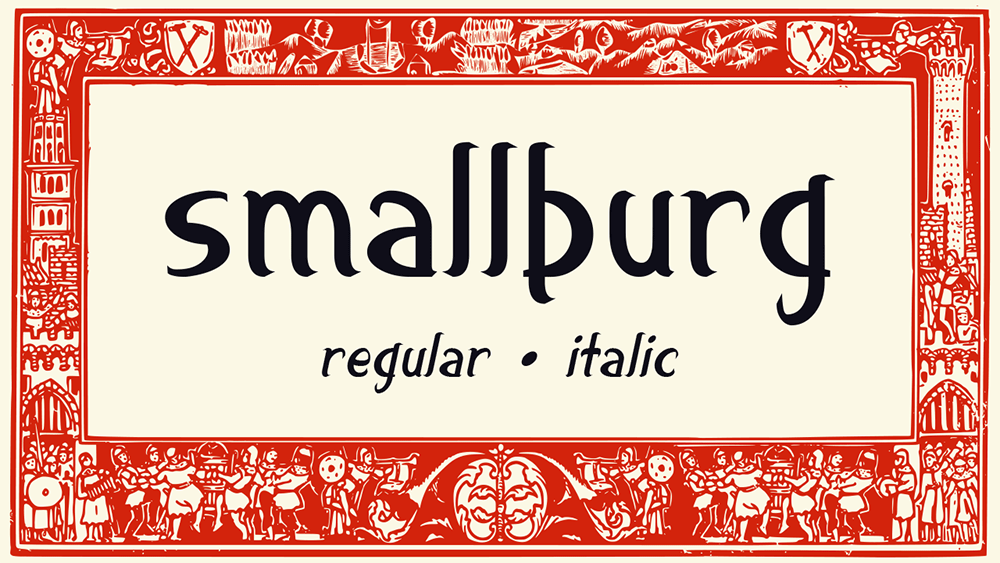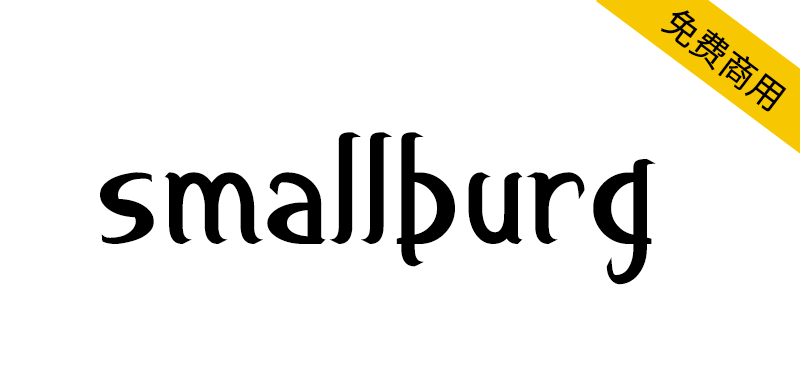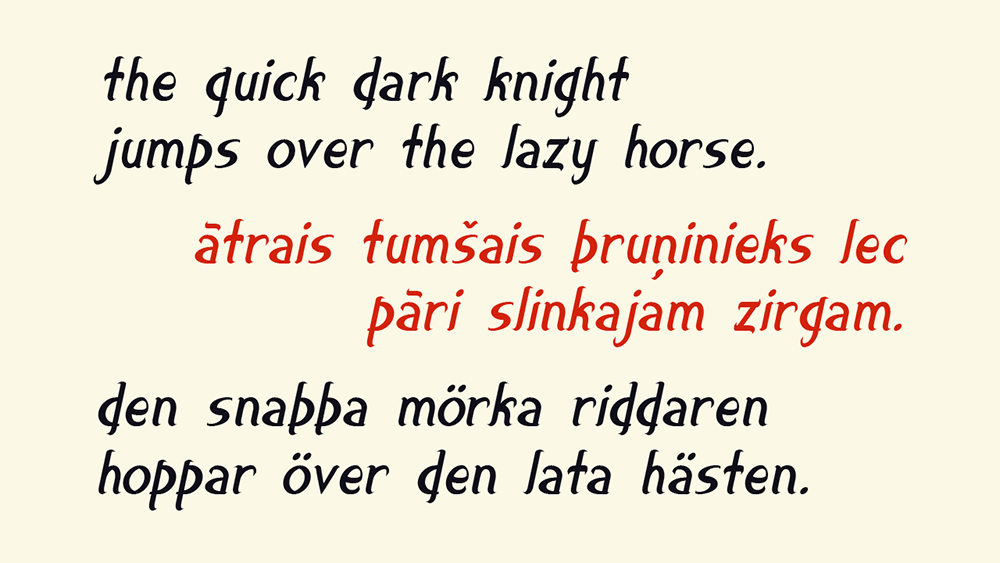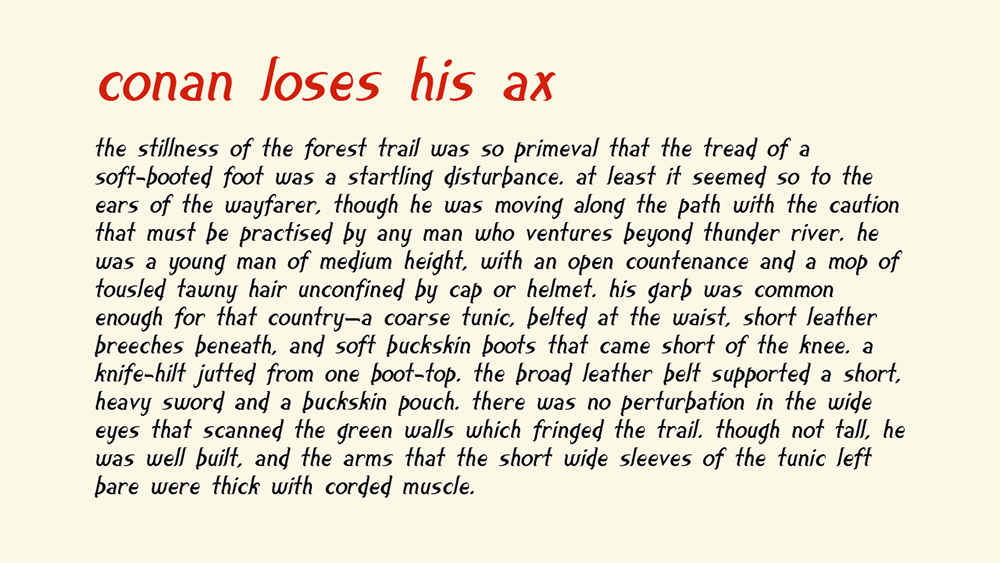
【Smallburg】手写风格免费英文字体, 2种样式和457个字形
Smallburg是一款根据SIL OFL协议发布的免费英文字体,手写风格,字母仅限小写(输入大写字母仍然显示小写),包含 2 种样式(Regular、Italic)和 457个字形。
支持 45 种语言:阿尔巴尼亚语、罗马尼亚语、阿斯图里亚斯语、布列塔尼语、加泰罗尼亚语、克罗地亚语、捷克语、丹麦语、荷兰语、英语、世界语、爱沙尼亚语、芬兰语、法语、加告兹语、德语、匈牙利语、冰岛语、伊博语、印度尼西亚语、意大利语、Khoekhoe、拉科塔语、拉丁语、拉脱维亚语、立陶宛语、马耳他语、马普顿贡语、北萨米语、挪威语、波兰语、葡萄牙语、罗马尼亚语、苏格兰盖尔语、斯洛文尼亚语、西班牙语、瑞典语、他加禄语、土耳其语、沃尔瑟德语、威尔士语、西弗里斯兰语、扎扎基语、祖鲁语。